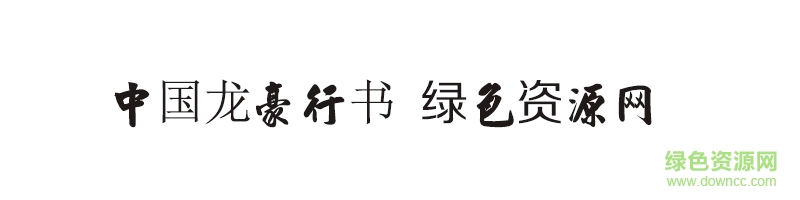
中國龍豪行書繁體字體一款中國龍字庫中的字體,是一款非常美觀的字體。非常適合用于名片設(shè)計(jì)、廣告設(shè)計(jì)、平面設(shè)計(jì)、雜志報(bào)刊等,有喜歡的朋友可以來綠色資源網(wǎng)下載使用!
中國龍豪行書是比較常用的藝術(shù)字體,此款字體線條流暢,簡潔易懂,不過它沒有完整的漢子詞庫,部分字體無法顯示。